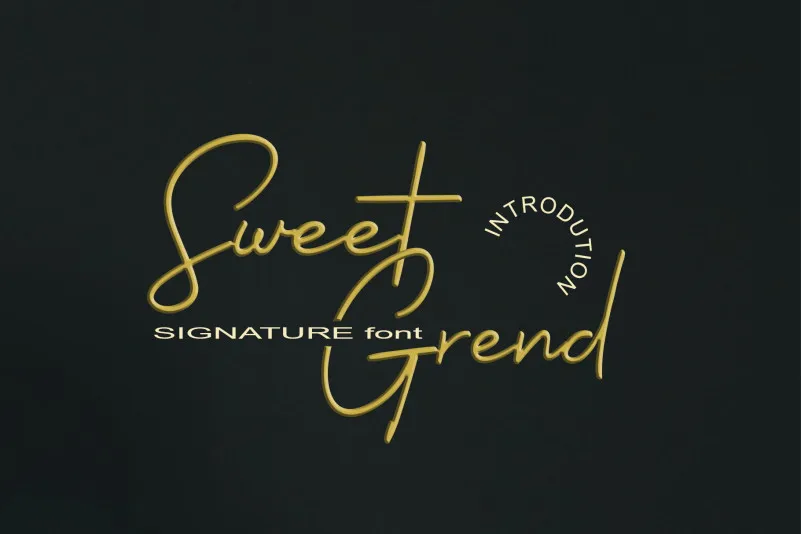
Sweetgrend Font – Fonte Grátis
Sweetgrend Font
Esta é uma fonte aquarela que traz personalidade para seus designs, especialmente indicada para os elementos mais delicados e expressivos como cartões de agradecimento, convites de casamento, cartas de cumprimentos, logotipos ou até mesmo artes gráficas em geral. Com seu estilo elegante e autêntico, esta fonte é perfeita para qualquer projeto que exige um toque único e delicado. Seja você criando cartões personalizados para casamentos, estampas de roupas com um ar romântico ou até mesmo uma identidade visual com uma pegada única, a Sweetgrend Font certamente enriquecerá seu trabalho gráfico. Além disso, sua versatilidade se torna ainda mais clara quando você usa esta fonte para criar seus próprios selos autênticos, que podem dar um toque único e memorável a qualquer documento ou arte digital. Com Sweetgrend Font, não importa qual é o seu projeto – seja ele grande ou pequeno – ela oferecerá uma solução elegante e única, criando memórias duradouras para seus clientes.